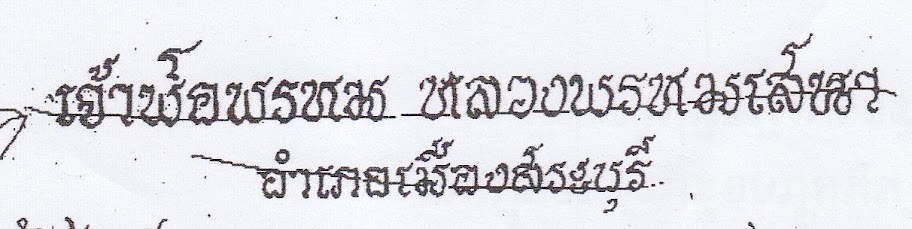
ฟอนด์นี้ฟอนด์อะไรค่ะ
ฟอนด์ตามรูปข้างล่างนี้ฟอนด์อะไรค่ะ ช่วยหน่อยนะค่ะ ขอบคุณค่ะ
ไม่ใช่ฟอนต์ครับ พยัญชนะตัวเดียวกัน แต่ละตัวหน้าตาไม่เหมือนกันเลยครับ
เป็นการเขียนมือครับ
ดูแล้วก็น่าเอามาทำฟอนต์เนาะ  :40: